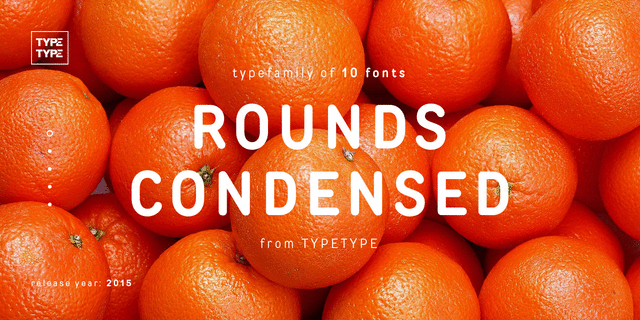
Rounds Condensed – это сжатая версия шрифта Rounds. Имеет добрый и нежный характер. Самый популярный набор начертаний: тонкое, светлое, нормальное, жирное, сверхжирное и их наклонные версии. Шрифт сделан таким образом, чтобы он мог применяться как в кратких текстах (логотип или заголовок), так и в полосе набора (абзац текста или статья в газете). Область применения: детские книжки, кафе, упаковка, сайты, ценники, логотипы, реклама, косметика, игрушки. Оптимизирован для применения на сайтах, в мобильных приложениях и печатной продукции. Шрифт разработан Иваном Гладких в студии TypeType Fonts в 2015 году.
Ассоциации c начертанием TT Rounds Condensed ThinКачества и характер:
деликатный, чистый, легкий, прохладный, холодный, свежий, модный, тонкий, современный, лаконичный, ясный, ровный, понятный, качественный, невесомый, прозрачный, интимный, точный, аккуратный, логичный, худой, стройный, практичный, нежный, воздушный, проволочный
парфюмерия, лосьон, красота, туалетная вода, шампунь, косметика, диета, чистота, гигиена, девайс, гаджет, инженер, чертеж, технологии, АСМР Стилистика:
Особенности семейства TT Rounds CondensedХит десятилетия: